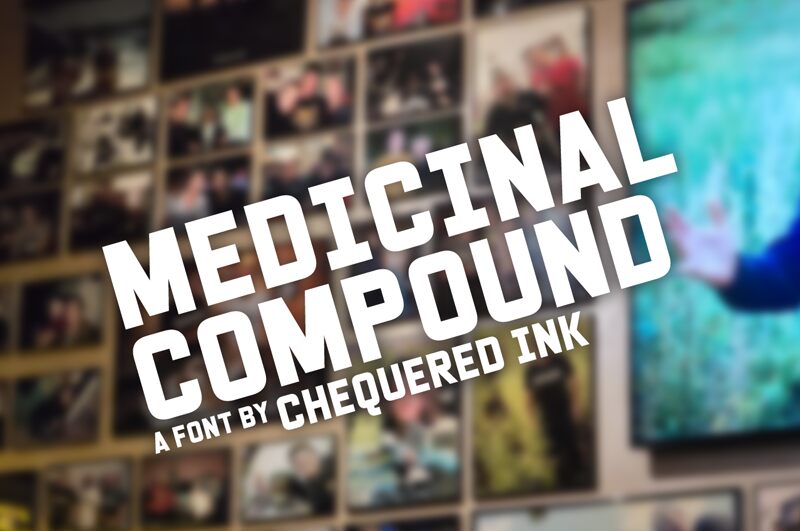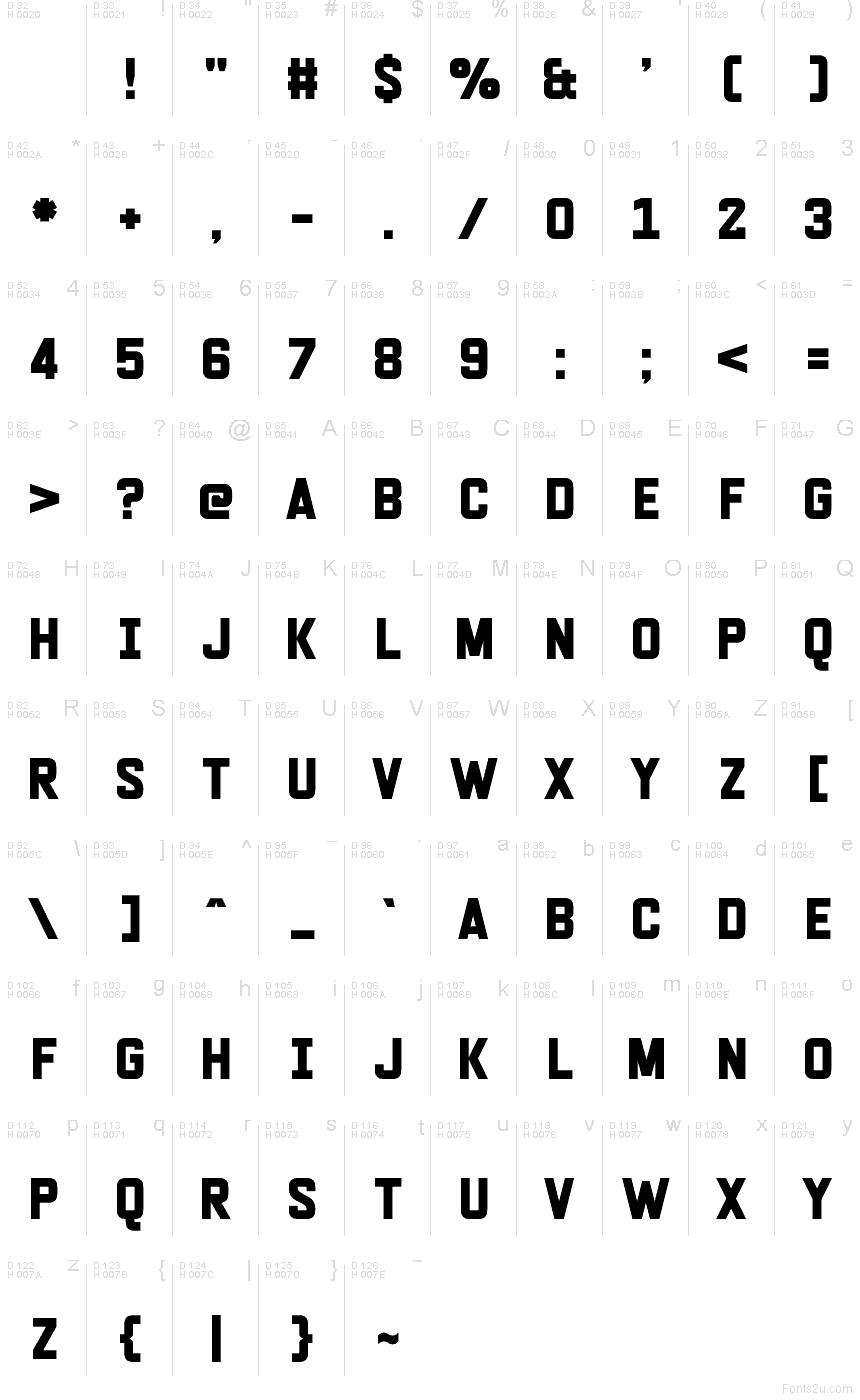
Medicinal Compound
Medicinal Compound od Chequered Ink je bezplatné písmo s medicínskou tematikou, které charakterizují čtvercové tvary, zkosené rohy a strohý vzhled připomínající klinické značení. Písmena jsou sestavena z rovných vertikál a blokových křivek s drobnými výřezy, které dodávají sadě výrazný, technický rytmus.
Medicinal Compound skvěle funguje na obalech léčiv, zdravotních plakátech, laboratorních štítcích, značkách z oblasti wellness i v uživatelských rozhraních se sci-fi lékařskou tématikou, protože jeho tvary působí strukturovaně a mírně klinicky, aniž by byly příliš dekorativní. Toto bezplatné písmo se také hodí pro výstražné štítky, informační cedule na akce a hlavní nadpisy, kde je důležitější přesný, technický tón než jemnost.